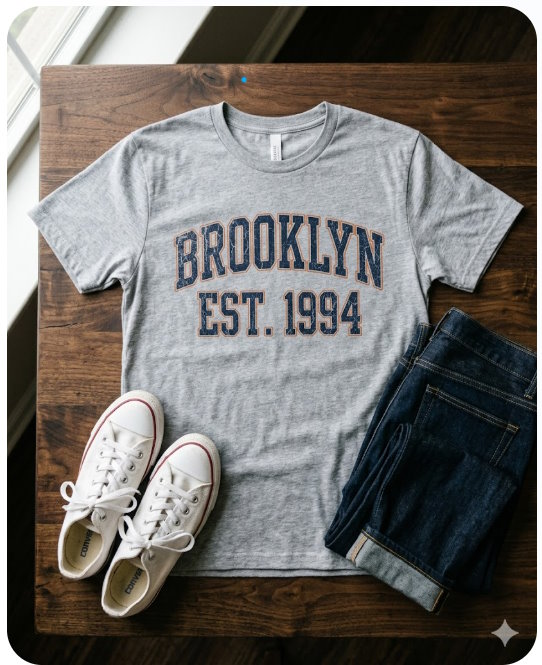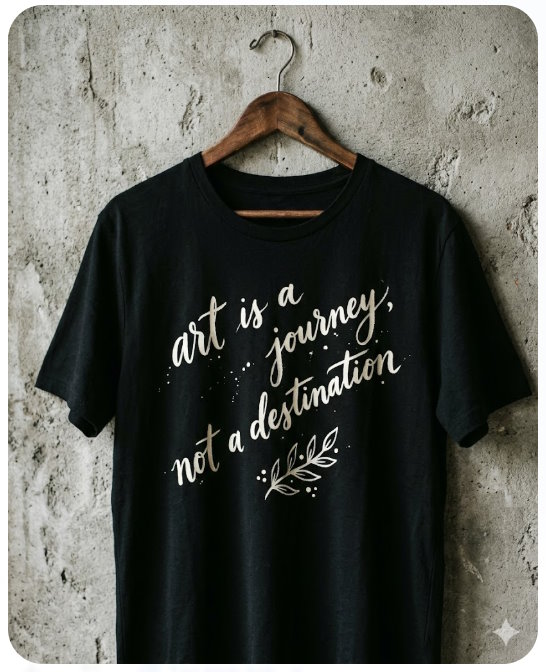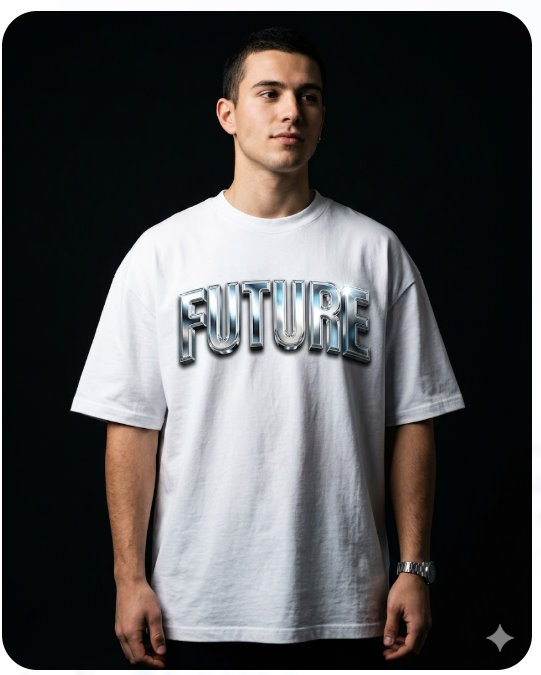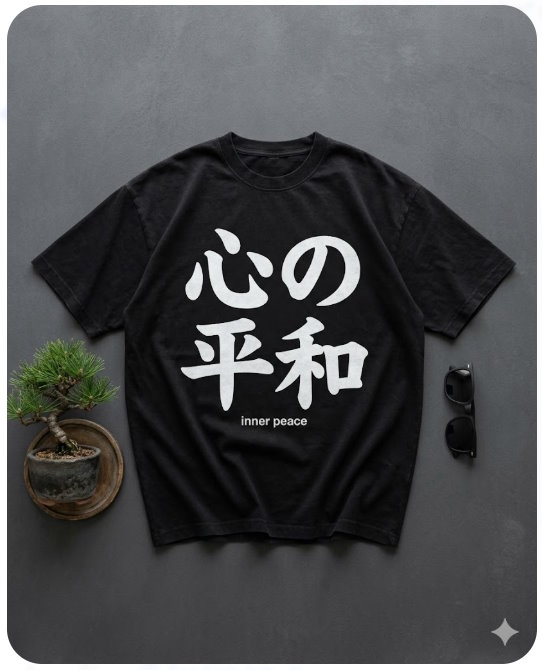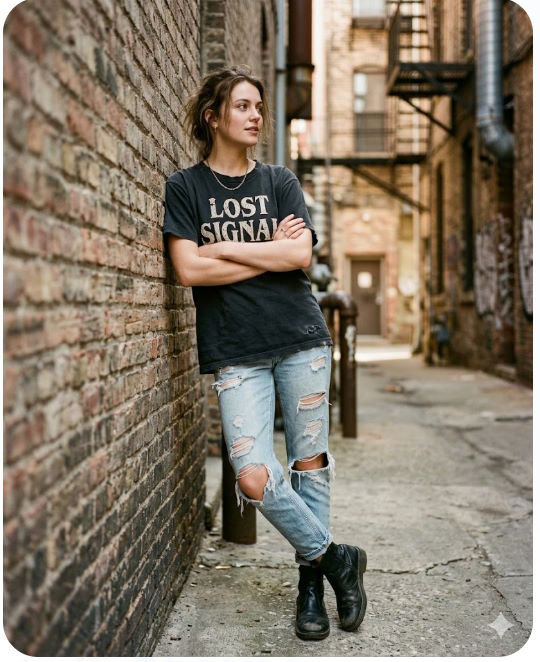
Prompt thiết kế font chữ độc đáo cho áo phông
Với mô hình tạo ảnh mới nhất của Gemini, bạn có thể thoải mái thiết kế kiểu chữ cho áo phông như ý muốn. Dưới đây là một số gợi ý viết prompt Gemini tạo kiểu chữ phong cách cho áo phông.
Kiểu chữ trên áo phông có thể quyết định sự thành công hay thất bại của toàn bộ thiết kế. Phông chữ phù hợp, bố cục hợp lý và phong cách phù hợp sẽ biến một chiếc áo phông đơn giản thành thứ mà mọi người thực sự muốn mặc. Và giờ đây, bạn có thể tạo ra những thiết kế này một cách trực quan bằng Gemini.
Prompt thiết kế chữ nghệ thuật đẹp cho áo phông
• Chữ in hoa cổ điển giống đồng phục trường đai học
• Chữ viết tay trên nền vải cotton đen
• Chữ nổi 3D mạ crom ấn tượng
• Chữ Kanji với phụ đề tiếng Anh
• Kiểu chữ phong cách Grunge cũ kỹ, sờn rách
Chữ in hoa cổ điển giống đồng phục trường đai học
Mẫu này mang đến kiểu chữ kinh điển trên áo đồng phục của trường học với những chữ in hoa to, nổi bật và kết cấu cũ kỹ.
**Prompt:**Hãy tạo ảnh phẳng một chiếc áo phông cổ tròn màu xám tro được đặt gọn gàng trên một chiếc bàn gỗ óc chó sẫm màu. Áo phông có chữ in hoa đậm kiểu đại học màu xanh hải quân với viền cam mỏng, ghi “BROOKLYN EST. 1994”. Các chữ cái có kết cấu in lụa hơi sờn rách với những vết nứt rõ ràng trên mực in. Một chiếc quần jeans tối màu được gấp gọn và một đôi giày thể thao vải bố màu trắng được đặt bên cạnh áo. Góc máy ảnh là từ trên xuống trong bố cục phẳng. Ánh sáng tự nhiên dịu nhẹ, đều từ cửa sổ gần đó tạo ra một bóng đổ nhẹ nhàng. Phong cách tối giản, gọn gàng với phong cách cổ điển kiểu Mỹ. Sử dụng tỷ lệ khung hình 4:5.
Prompt Gemini tạo chữ áo phông
Chữ viết tay trên nền vải cotton đen
Chữ viết tay luôn mang lại cảm giác cá nhân và chân thực. Prompt này thể hiện hoàn hảo cảm giác tự nhiên, như được viết bằng bút lông trên nền áo phông đen trơn.
Prompt: Hãy tạo cận cảnh một chiếc áo phông cotton đen treo trên móc gỗ, dựa vào bức tường bê tông thô. Chiếc áo có dòng chữ viết tay thanh lịch bằng mực trắng ngà, với những nét vẽ tự nhiên, vết mực bắn tung tóe và những điểm không hoàn hảo nhỏ tạo nên vẻ ngoài chân thực như được vẽ tay. Chữ viết chạy chéo trên ngực với một họa tiết trang trí nhỏ bên dưới. Góc máy chụp thẳng, ngang ngực. Ánh sáng studio dịu nhẹ, khuếch tán với một đèn chiếu ấm áp tạo hiệu ứng ánh sáng tinh tế trên vải. Phong cách nghệ thuật, độc lập, mang hơi hướng cá tính. Sử dụng tỷ lệ khung hình 4:5.
Chữ viết tay trên nền vải cotton đen
Chữ nổi 3D mạ crom ấn tượng
Để tạo phong cách đường phố hoặc lấy cảm hứng từ Y2K, chữ nổi 3D mạ crom trên áo phông trông vô cùng bắt mắt.
Prompt: Hãy tạo một bức ảnh sản phẩm với hình ảnh một chàng trai trẻ mặc áo phông trắng ngoại cỡ, đứng trước phông nền đen tuyền. Áo có dòng chữ nổi 3D mạ crom kim loại lớn ở ngực, ghi chữ “FUTURE” với hiệu ứng phản chiếu, bẻ cong ánh sáng và bề mặt kim loại lỏng bóng bẩy. Các chữ cái như nổi lên khỏi vải với hiệu ứng đổ bóng nhẹ. Chàng trai đứng thả lỏng hai tay, thân người hơi xoay sang góc ba phần tư. Máy ảnh đặt ngang ngực, cắt từ cổ đến eo. Ánh sáng studio ấn tượng với điểm nhấn sắc nét trên chữ mạ crom và độ tương phản sâu trong bóng tối. Phong cách thời trang đường phố mang hơi hướng tương lai, đậm chất biên tập với phông nền tối giản, sạch sẽ. Sử dụng tỷ lệ khung hình 4:5.
Chữ nổi 3D mạ crom ấn tượng
Chữ Kanji với phụ đề tiếng Anh
Việc kết hợp các ký tự Kanji với phụ đề tiếng Anh rõ ràng bên dưới sẽ tạo nên phong cách thời trang đường phố mà các thương hiệu đang ưa chuộng hiện nay.
**Prompt:**Hãy chụp ảnh một chiếc áo phông đen rộng thùng thình đã giặt, được trải phẳng trên bề mặt màu than mờ. Áo có các ký tự Kanji tiếng Nhật lớn, đậm màu, mực trắng ở giữa ngực, với dòng chữ tiếng Anh nhỏ hơn có nghĩa là “bình an trong tâm” được in bằng phông chữ sans-serif tối giản ngay bên dưới. Các nét Kanji có kết cấu hơi mềm mại, giống như thư pháp. Một chậu cây bonsai nhỏ trong chậu gốm và một cặp kính râm đen được đặt bên cạnh áo để làm đạo cụ. Góc máy ảnh là từ trên xuống, bố cục phẳng. Ánh sáng tự nhiên dịu nhẹ, tông màu lạnh với ít bóng. Phong cách thời trang đường phố hiện đại, sạch sẽ, lấy cảm hứng từ Nhật Bản. Sử dụng tỷ lệ khung hình 4:5.
Chữ Kanji với phụ đề tiếng Anh
Kiểu chữ phong cách Grunge cũ kỹ, sờn rách
Nếu bạn muốn có vẻ ngoài của một chiếc áo phông điển hình của ban nhạc cổ điển, đã qua sử dụng, gợi ý này tạo ra kiểu chữ grunge cũ kỹ, trông như đã được giặt cả trăm lần.
Prompt: Hãy chụp ảnh một cô gái trẻ mặc một chiếc áo phông đen cổ điển bạc màu với kiểu chữ sờn rách, nứt nẻ ở phía trước, ghi “LOST SIGNAL” bằng phông chữ serif thô ráp, không đều, với các cạnh mực bị bong tróc và vải lộ ra qua các chữ cái. Cô ấy đang dựa vào một bức tường gạch, khoanh tay, nhìn ra ngoài khung hình về phía bên phải với vẻ mặt thư thái, không bận tâm. Cô ấy mặc quần jean rách màu sáng và bốt cổ ngắn màu đen. Tóc cô ấy hơi rối và được vén ra sau một bên tai. Máy ảnh được đặt ngang tầm mắt, chụp thẳng với độ sâu trường ảnh nông. Ánh sáng tự nhiên ấm áp, nhạt màu chiếu xuyên qua một con hẻm. Cảm giác grunge thô ráp, đậm chất thập niên 90. Sử dụng tỷ lệ khung hình 4:5.
Kiểu chữ phong cách Grunge cũ kỹ, sờn rách